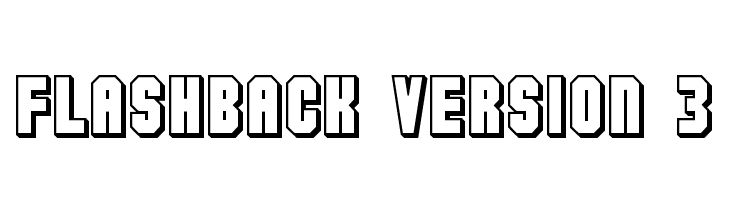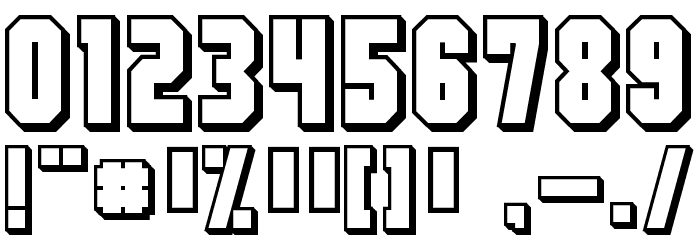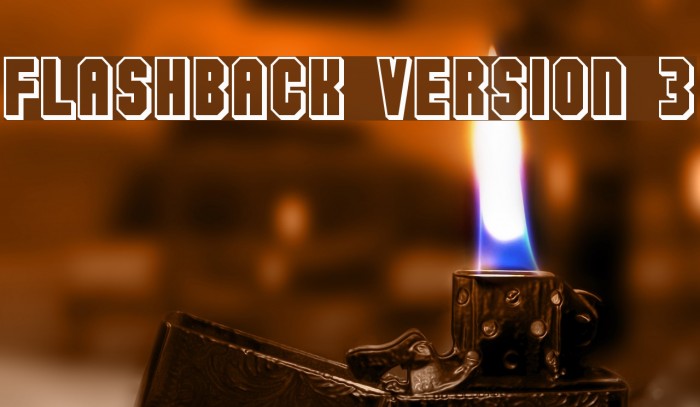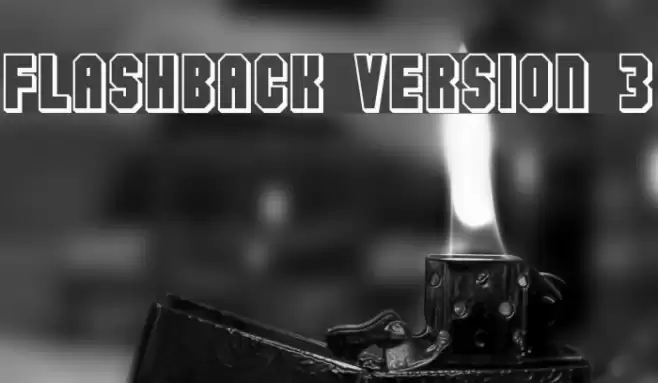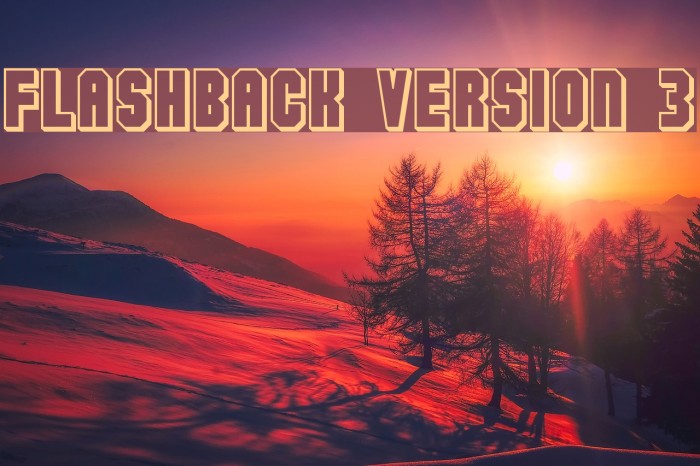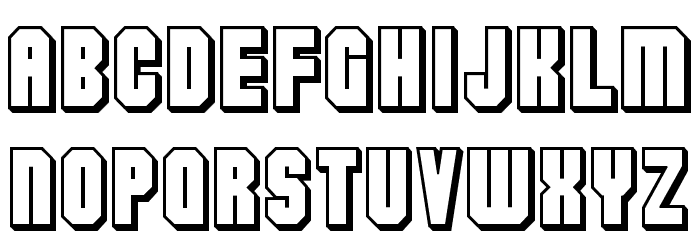
Flashback version 3 Font
Fonts by Jacob Fisher - www.pizzadude.dk
| 全体的なスタイル | Retro, Decorative |
| おすすめプロジェクト | This font is perfect for video game titles, posters, logos, and any design that aims to capture a retro or arcade feel. |